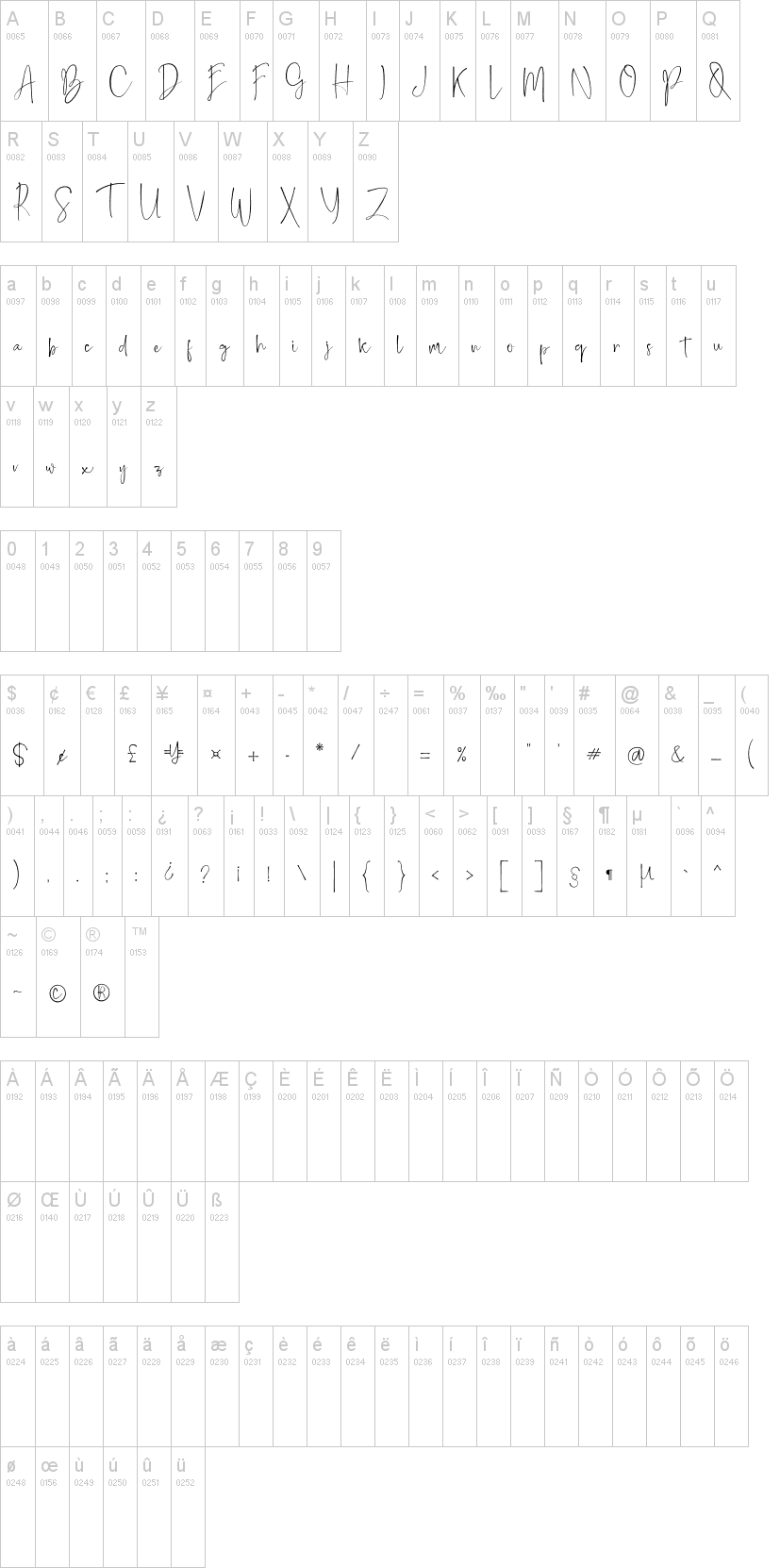
Belleson 是一种现代的字体,具有轻巧的外观和柔和的曲线。它的设计灵感来自美国西部的西式文化,以及拉丁美洲和西班牙的文化元素。它的字形曲线优雅,而且具有明显的美式风格,可以增加文本的可读性。这种字体可以用于任何文本,包括新闻、网页、广告和其他印刷品。它的独特的外观让它成为一种理想的字体,可以用于创造出独特的设计效果。内容介绍
Belleson是一款非常不错的手写艺术字体,具有很好的视觉感,适合于文化类的宣传设计、商业类品牌的广告和产品包装设计以及个性化文字排版等较多场景。